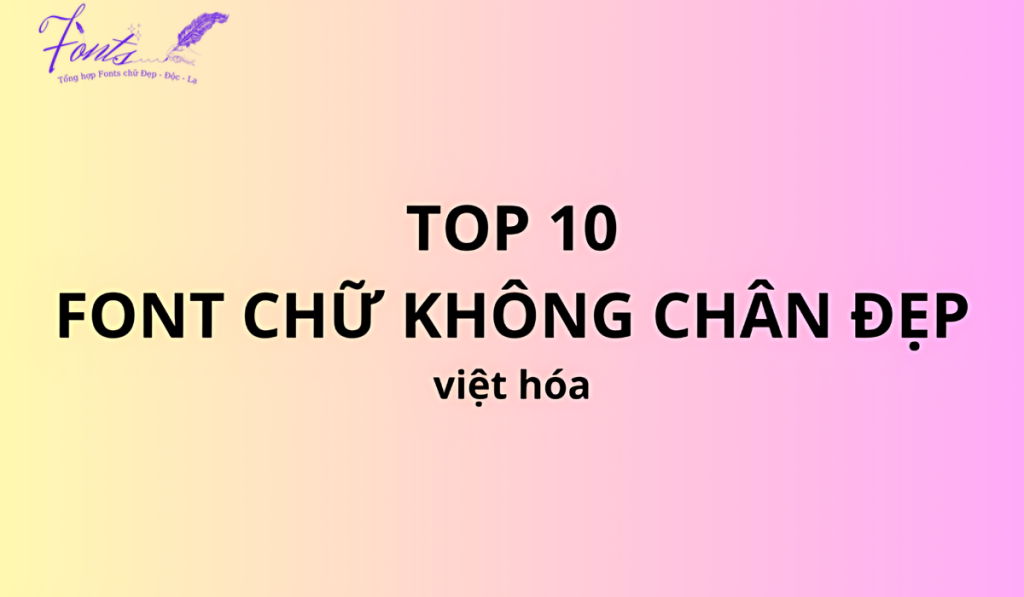
Font chữ không chân việt hóa
Font chữ không chân là một trong những loại phông chữ phổ biến và được sử dụng rộng rãi trong thiết kế đồ họa, thiết kế web và truyền thông ngày nay. Với đặc điểm nổi bật của bộ font chữ không chân là các ký tự có đường nét mượt mà, thanh mảnh, khoảng cách giữa các ký tự rộng rãi, thoáng mát, font chữ không chân tạo cảm giác hiện đại, trẻ trung và năng động cho các ấn phẩm. Trong bài viết này, chúng ta sẽ cùng tìm hiểu về định nghĩa font chữ không chân, top 10 font chữ không chân và link tải font chữ không chân đẹp năm 2024 nhé.
Font chữ không chân là gì? Tìm hiểu về đặc điểm và ứng dụng của font chữ không chân
Font chữ không chân hay còn gọi là font Sans Serif là một loại font chữ không có các đường nét nhỏ ở cuối mỗi ký tự. Đây là kiểu font chữ phổ biến và được ưa chuộng sử dụng trong thiết kế đồ họa hiện đại.
Font chữ không chân có các đặc điểm nổi bật như:
- Các nét chữ đơn giản, gọn gàng và dễ đọc
- Mang lại cảm giác hiện đại, trẻ trung
- Phù hợp sử dụng trên các phương tiện kỹ thuật số như website, ứng dụng di động
- Dễ kết hợp với các yếu tố thiết kế khác
Một số ví dụ tiêu biểu cho font chữ không chân bao gồm Arial, Helvetica, Futura, Proxima Nova. Các font chữ này thường được các thương hiệu lớn sử dụng trong thiết kế logo, bao bì sản phẩm hay giao diện website.
Khi sử dụng font chữ không chân, cần lưu ý:
- Chọn font chữ phù hợp với phong cách thiết kế và thông điệp muốn truyền tải
- Kết hợp màu sắc, kích thước chữ hợp lý để tạo điểm nhấn và thu hút người xem
- Không nên lạm dụng quá nhiều font chữ khác nhau trong cùng một thiết kế
Top 10 font chữ không chân Việt hóa và link tải
Font chữ không chân Helvetica
Font chữ Helvetica được coi là một trong những font chữ có tầm ảnh hưởng lớn nhất từ trước đến nay. Microsoft, Jeep đều đang rất ưa chuộng sử dụng font chữ này để thiết kế logo và nhấn mạnh thương hiệu của họ trong nhiều năm. Font chữ này trông rất mạnh mẽ và dễ nhìn. Với việc phát hành Helvetica vào năm 1957, Monotype đang củng cố di sản của một trong những font chữ sans-serif phổ biến và đẹp nhất từng được tạo ra.
Font chữ không chân Gotham
Font chữ Gotham là một trong những font chữ không chân phổ biến và được ưa chuộng nhất hiện nay. Font chữ này được nhà thiết kế Tobias Frere Jones tạo ra vào năm 2000, lấy cảm hứng từ những tấm biển hiệu ở New York vào giữa thế kỷ 20. Gotham sở hữu phong cách mạnh mẽ, hiện đại và dễ đọc với kích thước ký tự lớn, tròn. Tổng thống Barack Obama cũng sử dụng font chữ này trong chiến dịch tranh cử của mình.
Font Futura
Font chữ Futura là một trong những font chữ không chân nổi tiếng và được sử dụng rộng rãi nhất. Futura được thiết kế bởi Paul Renner vào năm 1927, với phong cách hiện đại, đơn giản và rõ ràng. Kiểu chữ này dựa trên các hình dạng hình học cơ bản như hình tròn, hình vuông và tam giác.
Futura có nhiều phiên bản khác nhau như Futura Light, Futura Book, Futura Medium, Futura Demi, Futura Bold và Futura Extra Bold. Điều này giúp Futura trở nên linh hoạt và đáp ứng được nhiều mục đích sử dụng khác nhau.
Với thiết kế tối giản và dễ đọc, Futura thường được sử dụng trong các ấn phẩm, quảng cáo, bao bì sản phẩm và thiết kế logo. Nhiều thương hiệu nổi tiếng như Volkswagen, Ikea, Swissair và HP đã sử dụng Futura làm font chữ chính trong bộ nhận diện thương hiệu của mình.
Font chữ không chân Việt hóa Arial
Font chữ Arial Việt hóa là một trong những font chữ không chân phổ biến nhất hiện nay. Font chữ này có thiết kế đơn giản, dễ đọc và thân thiện với người dùng. Arial Việt hóa phù hợp để sử dụng cho các tiêu đề, nội dung và thiết kế đồ hoạ trên website.
Font chữ không chân Roboto
Phông chữ dễ đọc Roboto là một trong những font chữ không chân phổ biến nhất hiện nay. Font chữ Roboto được thiết kế bởi Christian Robertson và phát hành bởi Google vào năm 2011. Với thiết kế đơn giản, rõ ràng và dễ đọc, Roboto nhanh chóng trở thành font chữ mặc định trên hệ điều hành Android, Roboto có nhiều phiên bản khác nhau như Roboto Regular, Roboto Medium, Roboto Bold và Roboto Condensed.